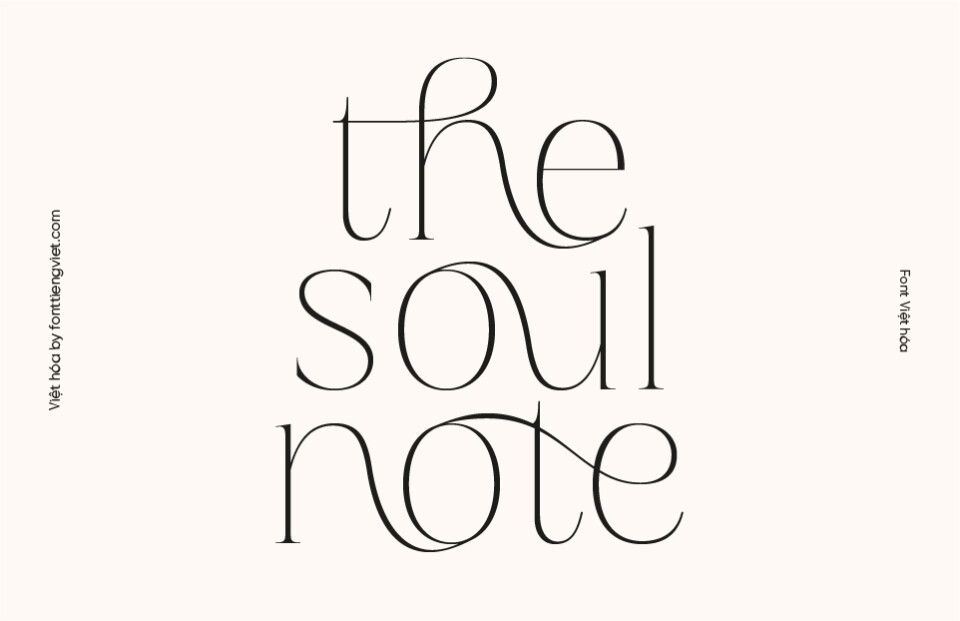
Giới thiệu về Font Việt hóa 1FTV VIP Soul Note Display
Trong thế giới thiết kế đồ họa hiện đại, việc tìm kiếm một bộ Font Chữ ấn tượng là ưu tiên hàng đầu của các bạn học sinh và thầy cô. Font Việt hóa 1FTV VIP Soul Note Display nổi lên như một lựa chọn hoàn hảo nhờ phong cách thiết kế phóng khoáng và mang đậm dấu ấn cá nhân. Đây là kiểu chữ Display với những đường nét uốn lượn tự nhiên, giúp các bài thuyết trình hay báo tường trở nên sinh động và lôi cuốn hơn bao giờ hết. Bộ font này đã được tối ưu hóa bảng mã tiếng Việt, giúp người dùng dễ dàng sử dụng trên các phần mềm phổ biến mà không lo lỗi hiển thị.
Đặc điểm nổi bật của Font Việt hóa 1FTV VIP Soul Note Display
Thiết kế mang tính nghệ thuật cao
Đúng như tên gọi Soul Note, bộ font này mang đến cảm giác như những nốt nhạc tâm hồn được viết tay tỉ mỉ. Các nét thanh và nét đậm được kết hợp hài hòa, tạo nên sự cân đối nhưng vẫn giữ được vẻ phá cách. Điều này đặc biệt phù hợp cho các tiêu đề lớn, banner sự kiện trường học hoặc bìa giáo án điện tử cần sự sáng tạo.
Khả năng ứng dụng đa dạng trong học tập
Không chỉ dùng cho thiết kế chuyên nghiệp, Font Việt hóa 1FTV VIP Soul Note Display còn rất hữu ích trong môi trường giáo dục. Các bạn học sinh có thể dùng font này để làm thiệp tặng thầy cô, trang trí sơ đồ tư duy hoặc tạo các tiêu đề nổi bật cho bài làm nhóm. Kiểu chữ này giúp truyền tải thông điệp một cách mềm mại và gần gũi hơn.
Lưu ý khi sử dụng Font Việt hóa 1FTV VIP Soul Note Display
Để phát huy tối đa vẻ đẹp của bộ font này, bạn nên kết hợp nó với các phông chữ không chân (Sans-serif) đơn giản ở phần nội dung. Việc này tạo ra sự tương phản thị giác thú vị, giúp người xem tập trung vào tiêu đề chính. Hãy tải ngay Font Miễn Phí, Font Việt Hóa, Font Việt hóa 1FTV VIP Soul Note Display để bắt đầu hành trình sáng tạo những tác phẩm mang đậm phong cách riêng của mình nhé.